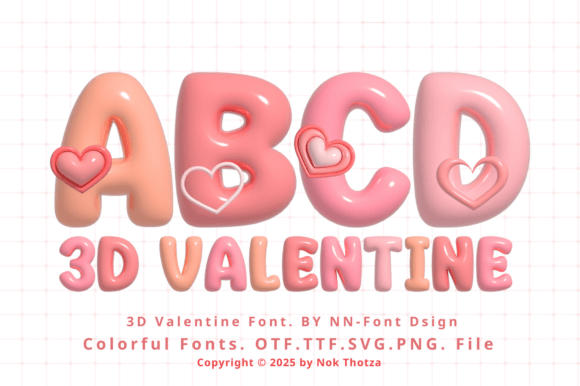
3d Valentine
การค้นหาองค์ประกอบการออกแบบที่เหมาะสมอาจเป็นเรื่องท้าทาย แต่ 3d Valentine นำเสนอคอลเลกชันที่โดดเด่นซึ่งช่วยยกระดับงานของคุณได้ทันที
ไม่ว่าคุณจะสร้างผลิตภัณฑ์ POD (Print on Demand) คำเชิญงานแต่งงาน หรือกราฟิกโซเชียลมีเดีย 3d Valentine ก็เหมาะสมอย่างยิ่ง